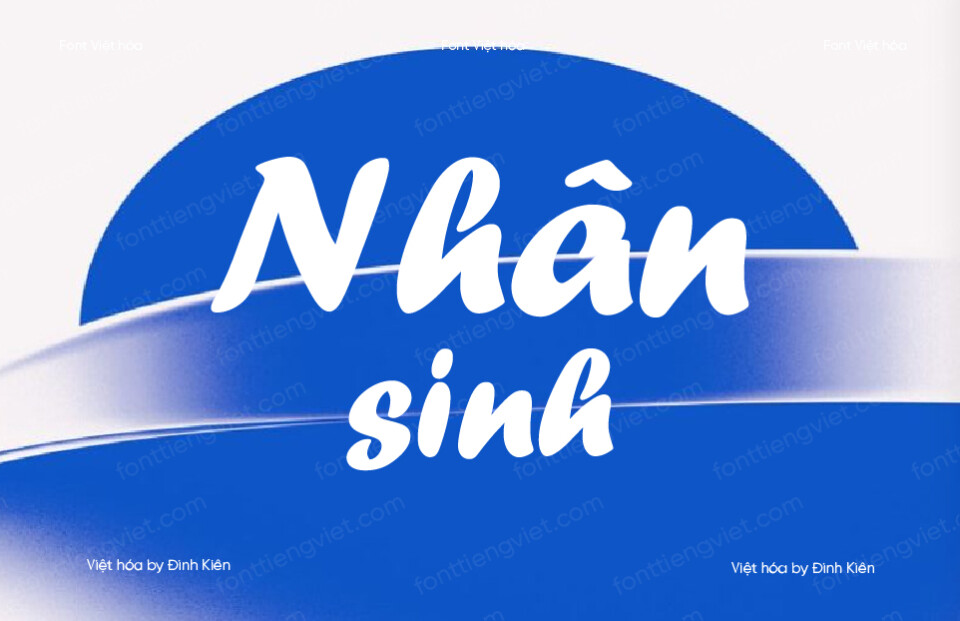
Trong thế giới rộng lớn của typography và thiết kế đồ họa, việc lựa chọn một Font Chữ phù hợp không chỉ định hình phong cách mà còn truyền tải thông điệp một cách hiệu quả. Với những người làm việc với tiếng Việt, thách thức càng lớn hơn khi cần tìm kiếm các bộ font đã được Việt hóa hoàn chỉnh, đảm bảo hiển thị đúng và đẹp các dấu tiếng Việt. Và một trong những cái tên nổi bật, được cộng đồng thiết kế đồ họa và người dùng đánh giá cao, chính là Font Việt hóa UTM Forte. Đây không chỉ là một phông chữ đơn thuần mà còn là một công cụ mạnh mẽ, mang đến vẻ đẹp cổ điển, mạnh mẽ và đầy cá tính cho bất kỳ dự án nào. Bài viết này sẽ đi sâu vào khám phá những đặc điểm nổi bật, lý do UTM Forte lại trở thành lựa chọn yêu thích, cũng như hướng dẫn chi tiết cách tải và sử dụng font chữ đặc biệt này một cách tối ưu nhất.
Font Việt hóa UTM Forte: Nét Độc Đáo Làm Nên Thương Hiệu
Đặc điểm nổi bật của Font Việt hóa UTM Forte
Font Việt hóa UTM Forte nổi bật với phong cách mạnh mẽ, đậm chất cổ điển nhưng không kém phần hiện đại. Các đường nét của font được thiết kế dứt khoát, với độ dày vừa phải, tạo cảm giác vững chãi và rõ ràng. Đặc biệt, phiên bản Việt hóa của UTM Forte đã được tối ưu hóa cẩn thận để hỗ trợ đầy đủ các ký tự có dấu của tiếng Việt, đảm bảo văn bản hiển thị mượt mà, không bị lỗi font hay mất dấu, điều mà nhiều font gốc nước ngoài thường gặp phải. Sự kết hợp giữa vẻ ngoài mạnh mẽ và khả năng hỗ trợ tiếng Việt hoàn hảo khiến UTM Forte trở thành một lựa chọn lý tưởng cho nhiều mục đích khác nhau, từ thiết kế logo, tiêu đề, poster cho đến các ấn phẩm truyền thông đòi hỏi sự ấn tượng và chuyên nghiệp.
Tại sao Font Việt hóa UTM Forte lại được ưa chuộng?
Có nhiều lý do khiến Font Việt hóa UTM Forte được cộng đồng thiết kế đồ họa và người dùng cá nhân yêu thích. Thứ nhất, tính thẩm mỹ cao của nó giúp các tác phẩm trở nên nổi bật và có điểm nhấn. Font Forte mang một vẻ đẹp phóng khoáng nhưng vẫn rất trang trọng, dễ dàng gây ấn tượng ngay từ cái nhìn đầu tiên. Thứ hai, khả năng Việt hóa hoàn chỉnh là một điểm cộng rất lớn, giải quyết triệt để nỗi lo về hiển thị tiếng Việt của các nhà thiết kế. Không còn những ký tự bị lỗi, không còn phải loay hoay căn chỉnh thủ công từng dấu. Thứ ba, UTM Forte rất linh hoạt trong ứng dụng. Dù bạn đang thiết kế một tấm thiệp mời cưới, một poster quảng cáo sự kiện, một bìa sách hay một banner cho website, font chữ này đều có thể “biến hóa” để phù hợp, mang lại hiệu quả thị giác cao. Với sự mạnh mẽ và rõ ràng, UTM Forte cũng rất phù hợp cho các tiêu đề lớn, tạo sự thu hút và dễ đọc, đặc biệt trong các tài liệu học tập, báo cáo hay slide thuyết trình của học sinh, sinh viên, giúp thông tin được trình bày một cách mạch lạc và chuyên nghiệp.
Ứng Dụng Thực Tiễn Của Font Việt hóa UTM Forte Trong Thiết Ký và Học Tập
Font Việt hóa UTM Forte trong thiết kế đồ họa
Trong lĩnh vực thiết kế đồ họa, Font Việt hóa UTM Forte là một công cụ vô cùng linh hoạt. Nó thường được sử dụng để tạo ra các tiêu đề, slogan, và logo mạnh mẽ, ấn tượng. Với đặc trưng đậm nét và rõ ràng, font này rất phù hợp cho các chiến dịch quảng cáo, thiết kế poster, banner sự kiện, hay thậm chí là bao bì sản phẩm. Nhiều nhà thiết kế cũng tận dụng UTM Forte để tạo điểm nhấn cho các ấn phẩm in ấn như danh thiếp, brochure, hay thiệp mời, mang lại vẻ sang trọng và độc đáo. Sự Việt hóa hoàn chỉnh giúp các nhà thiết kế tự tin sáng tạo mà không lo ngại về vấn đề hiển thị ngôn ngữ.
Font Việt hóa UTM Forte và giá trị giáo dục
Không chỉ giới hạn trong lĩnh vực thiết kế chuyên nghiệp, Font Việt hóa UTM Forte còn có giá trị ứng dụng trong môi trường giáo dục, đặc biệt là với học sinh, sinh viên và giáo viên. Khi tạo ra các bài thuyết trình, báo cáo khoa học, hay tài liệu học tập, việc sử dụng một font chữ rõ ràng, dễ đọc như UTM Forte có thể giúp tăng tính chuyên nghiệp và thu hút sự chú ý của người đọc. Đặc biệt, đối với các đề tài liên quan đến lịch sử, văn hóa hoặc các sự kiện cần sự trang trọng, UTM Forte có thể truyền tải một cảm giác cổ điển và đáng tin cậy. Nó giúp các em học sinh trung học phổ thông trình bày dự án tốt nghiệp, bài luận một cách mạch lạc, dễ hiểu, góp phần nâng cao chất lượng bài thi và dự án cuối kỳ.
Tóm lại, Font Việt hóa UTM Forte không chỉ là một phông chữ đẹp mà còn là một giải pháp hữu hiệu cho những ai đang tìm kiếm sự kết hợp giữa tính thẩm mỹ, sự mạnh mẽ và khả năng hỗ trợ tiếng Việt hoàn hảo. Với những đặc điểm nổi bật, khả năng ứng dụng đa dạng từ thiết kế đồ họa chuyên nghiệp đến các tài liệu học tập, và quy trình cài đặt đơn giản, UTM Forte xứng đáng là một công cụ không thể thiếu trong bộ sưu tập Font Chữ của bạn. Việc nắm vững cách sử dụng và tối ưu font chữ này chắc chắn sẽ mở ra nhiều cơ hội sáng tạo mới, giúp các dự án của bạn trở nên ấn tượng và chuyên nghiệp hơn bao giờ hết, góp phần vào thành công trong học tập cũng như công việc.